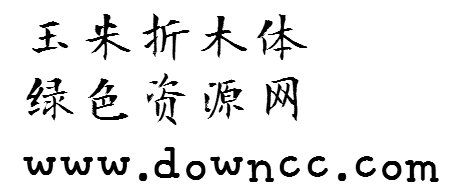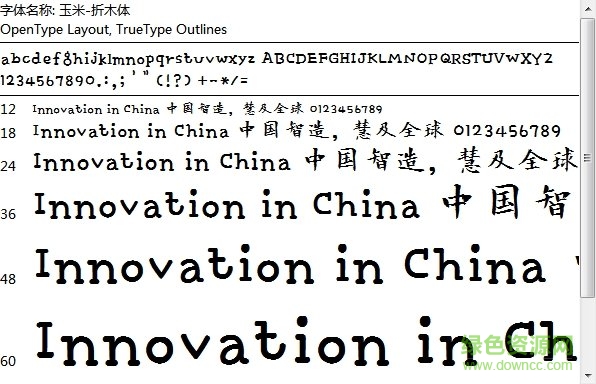
折木體是玉米字體系列的一款古風字體,有著清晰凌厲的筆畫,和干凈簡明的文風,看起來十分舒適清爽,快來綠色資源網(wǎng)試試吧!
折木體中文筆跡仿若樹枝版筆直中正,英文如流水般陸地部分而清揚,但字庫不是十分完整,部分文字需要轉(zhuǎn)換為范文狀態(tài)方可使用!
折木體字跡墨采飛動、風度超逸,精麗妍美而又自然流便,看上去十分美觀,整體效果非常統(tǒng)一,可以廣泛應(yīng)用于名片設(shè)計、新聞媒體、宣傳海報!